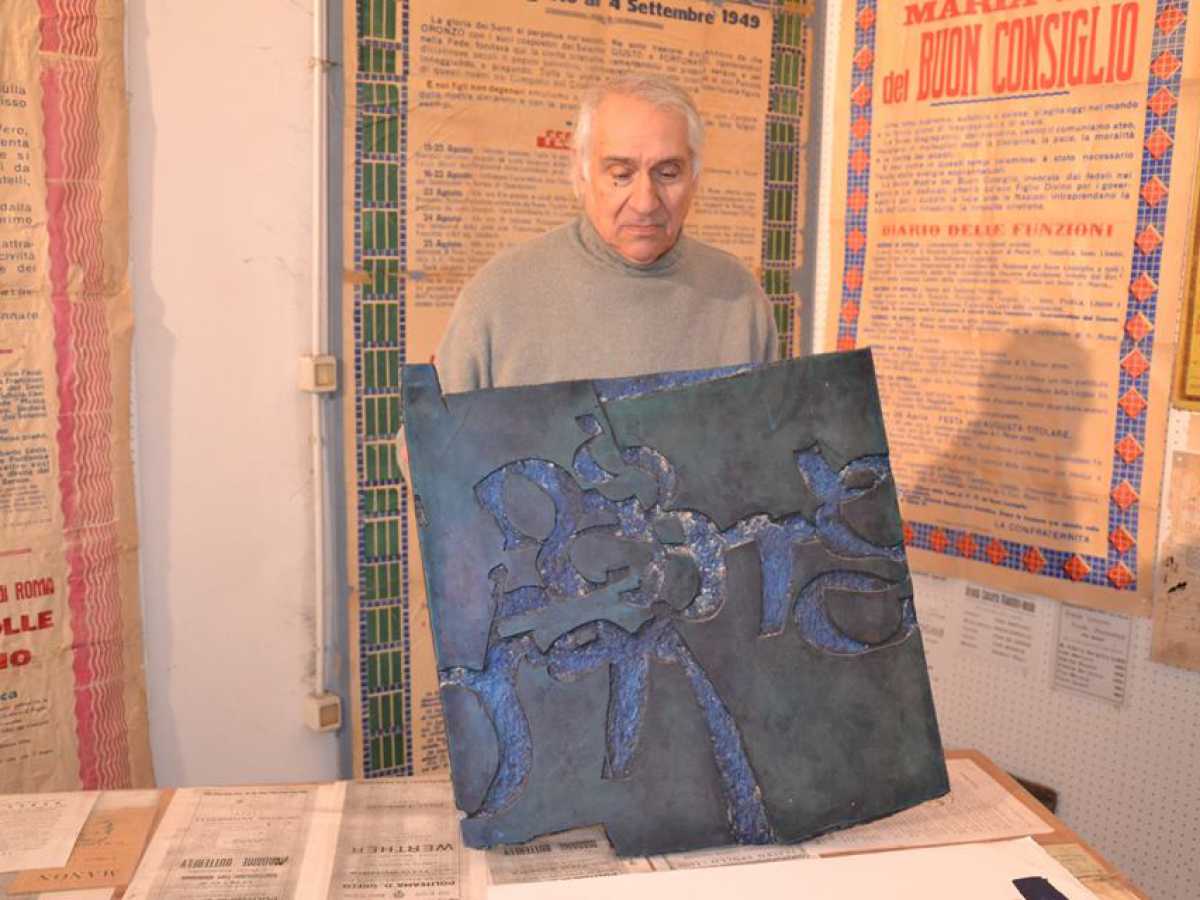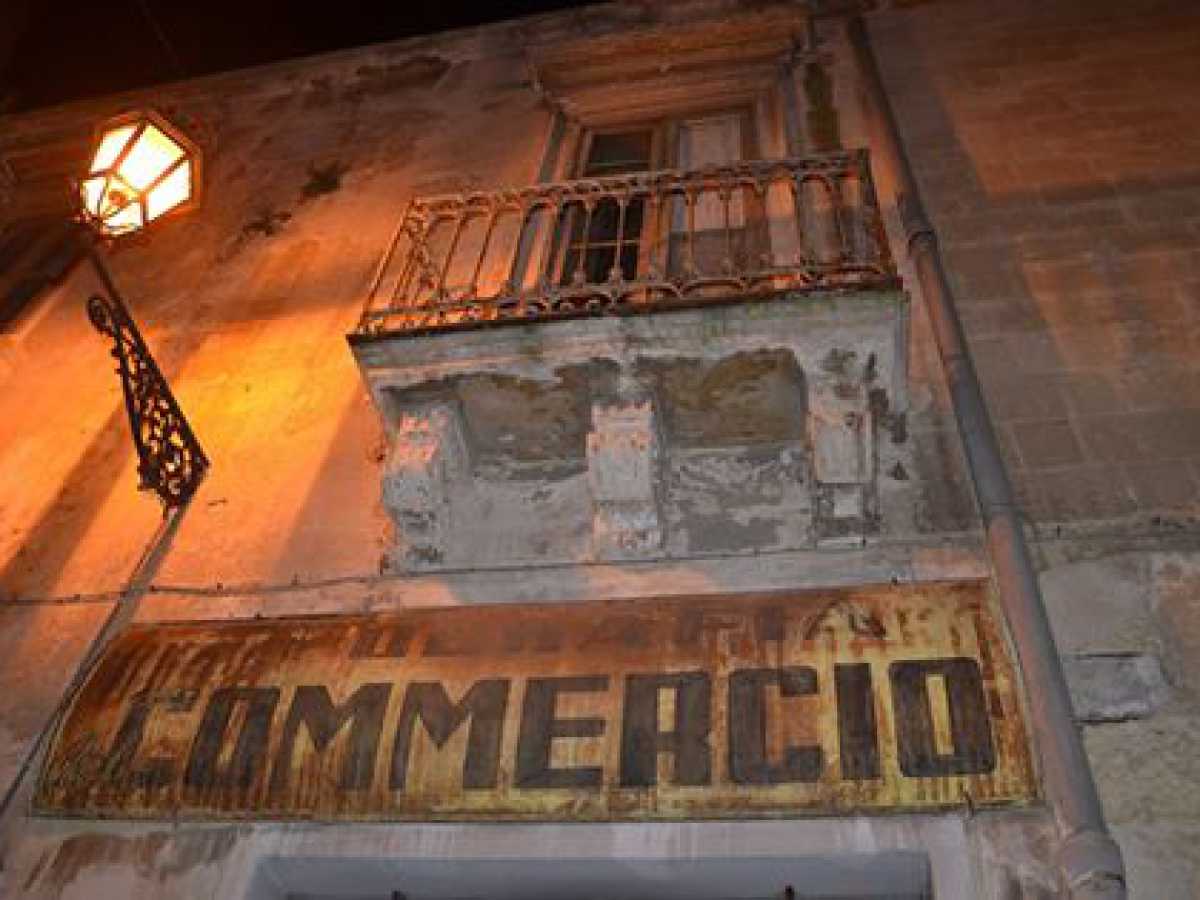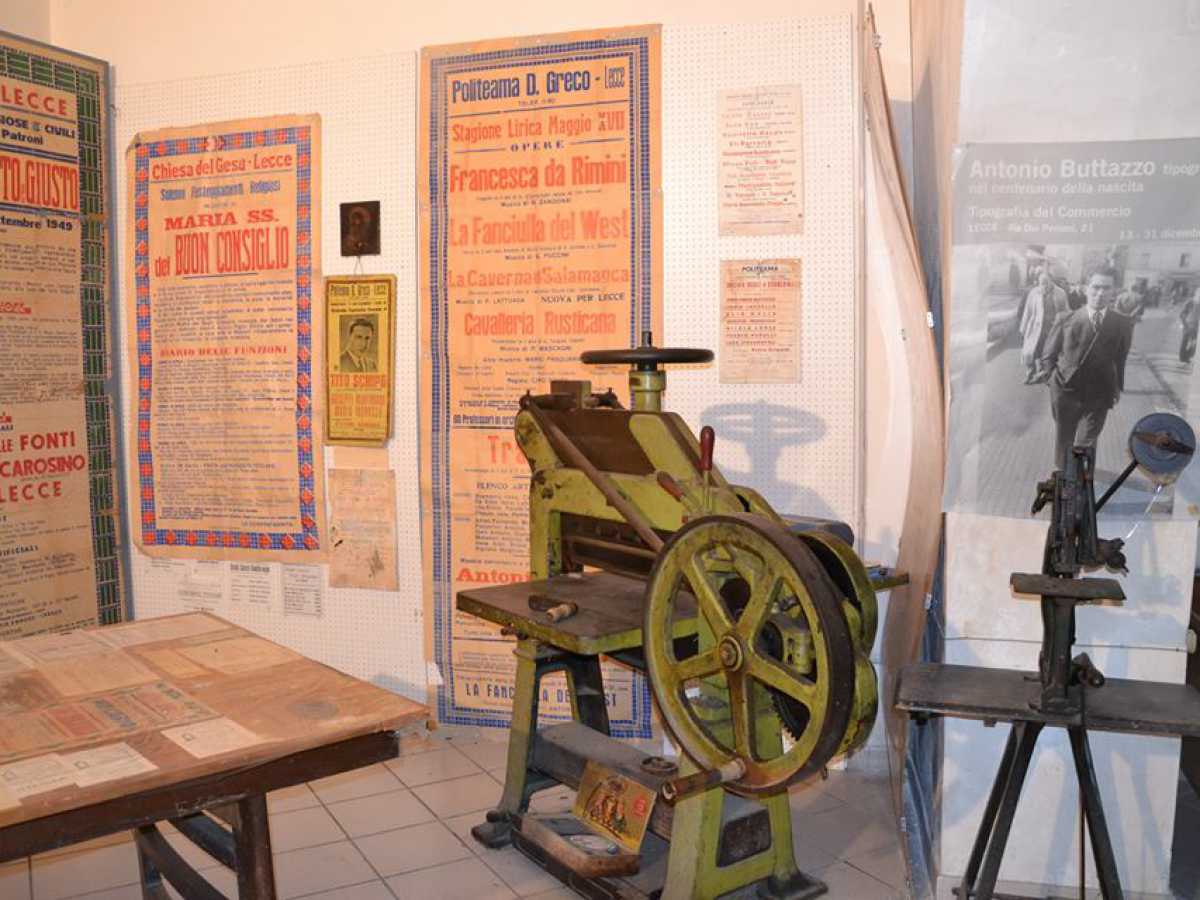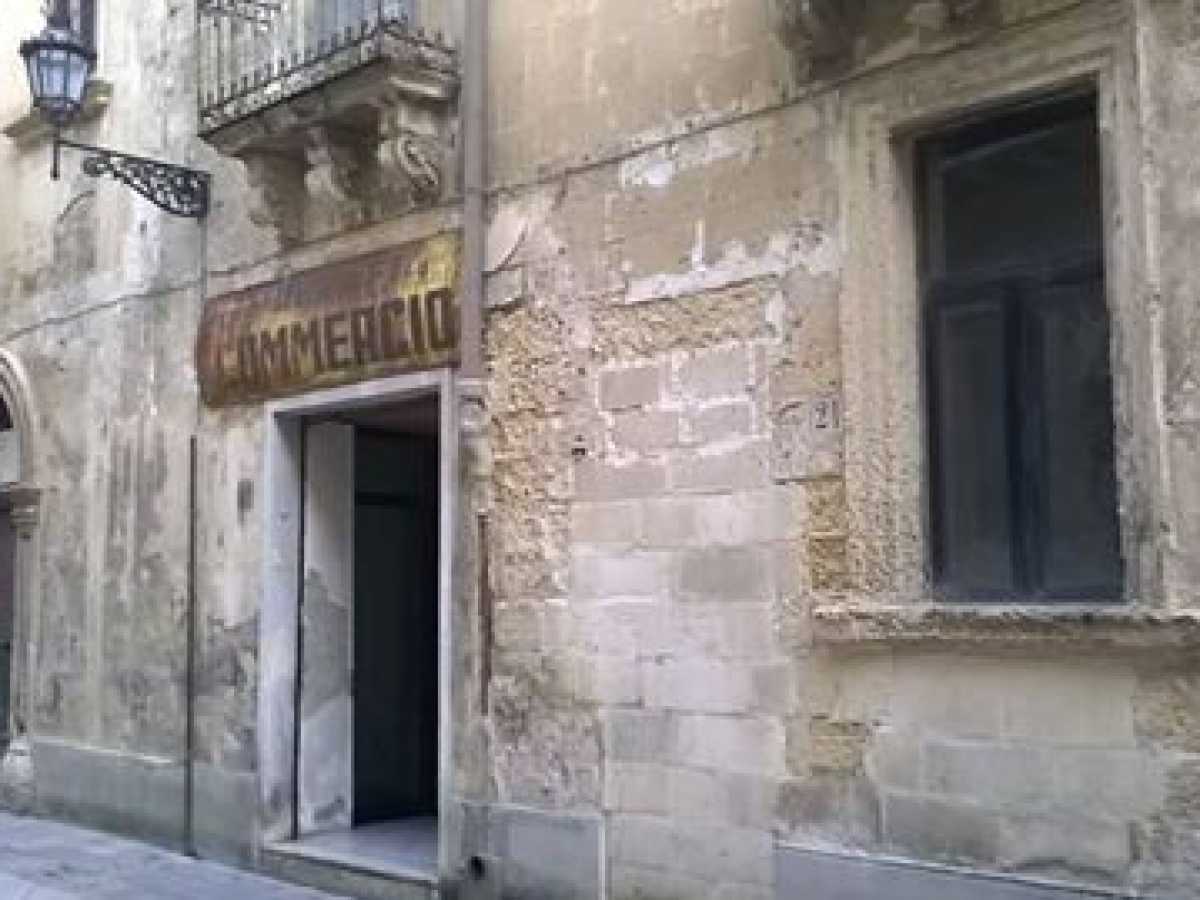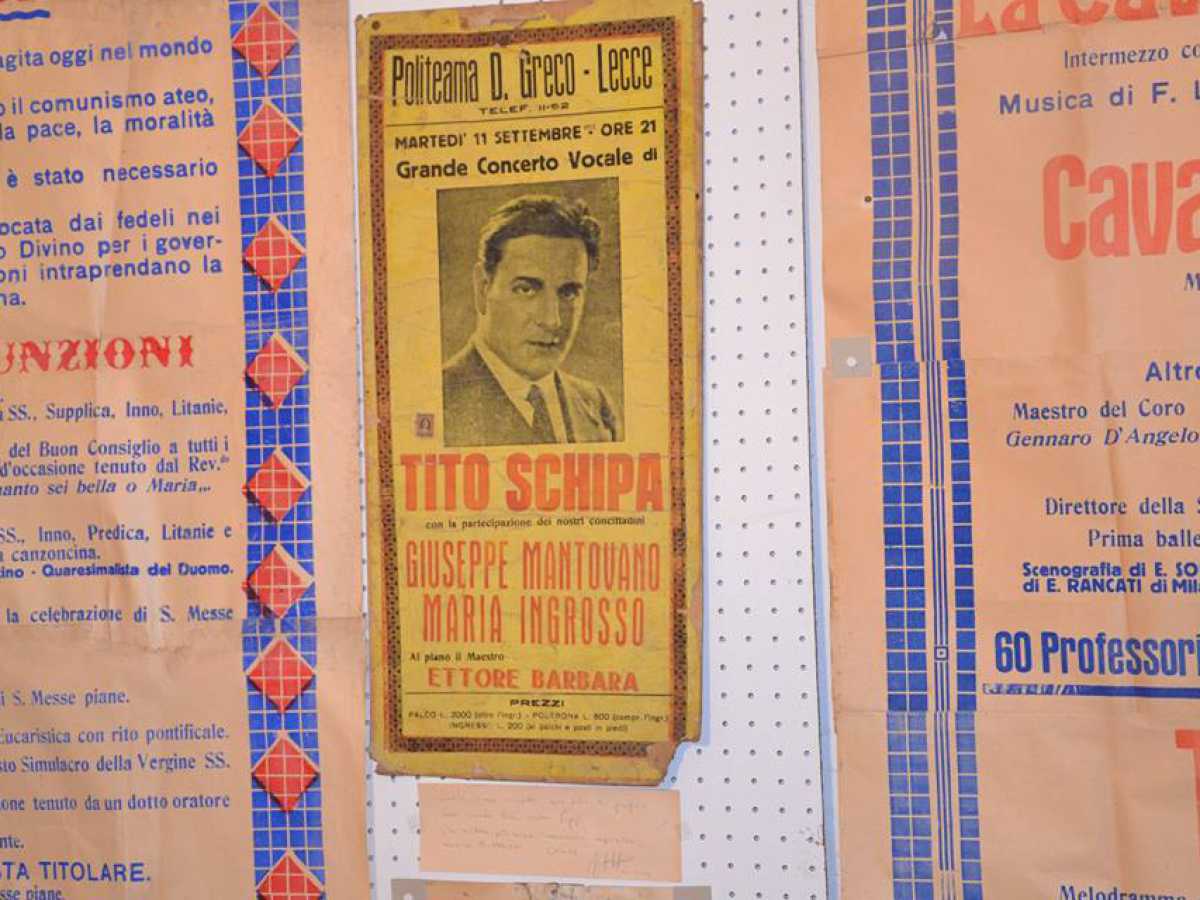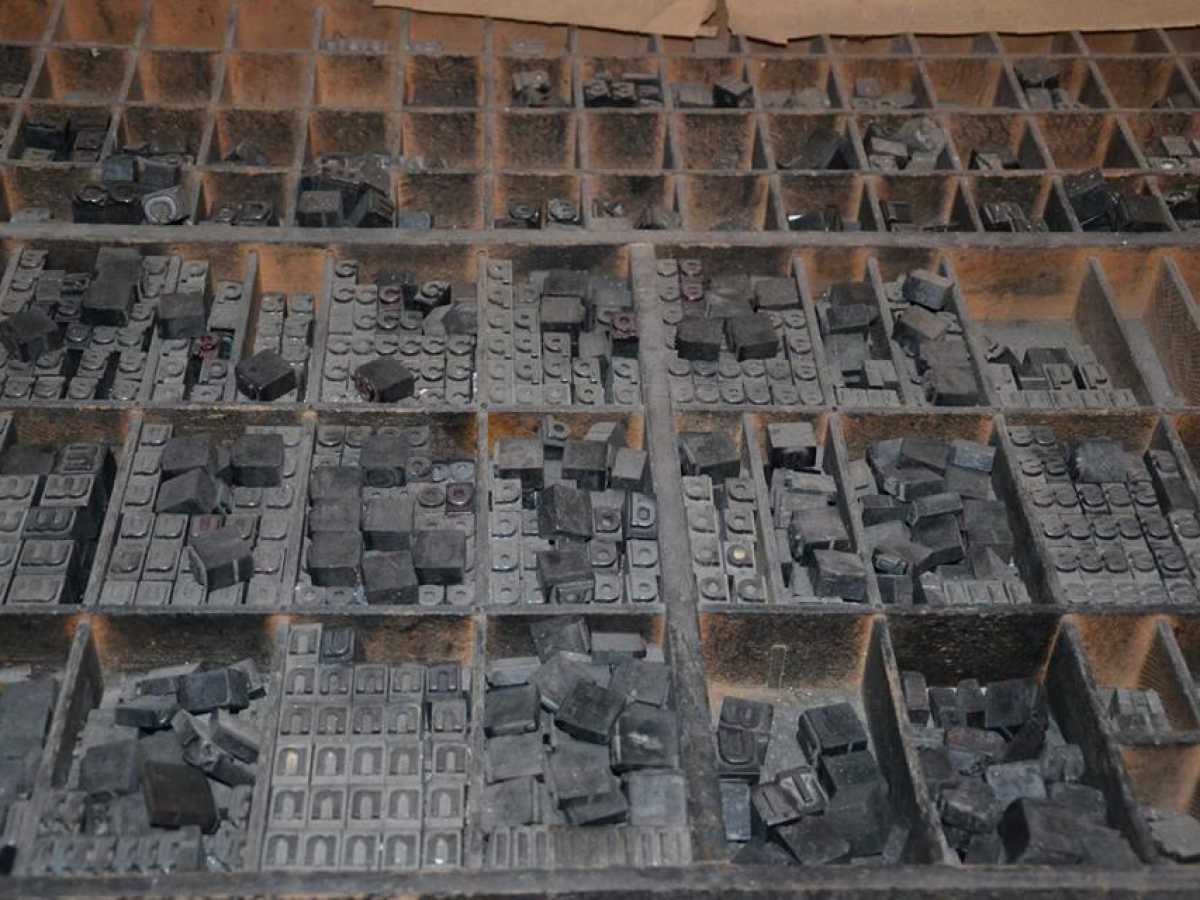
Lecce, la Tipografia del Commercio
L'antica Tipografia del Commercio a Lecce con macchinari dell'800 e del 900 ancora in uso e manifesti e locandine stampate come si faceva una volta, senza l'ausilio dei computer
Il palazzo in cui ha sede la Tipografia del commercio a Lecce in via dei Perroni
L'insegna del 1934, oramai annerita, all'ingresso della tipografia
I caratteri mobili conservati e utilizzati presso la Tipografia del commercio
Esempio dei caratteri formato elefante inventati dal tipografo Antonio Buzzato
La pedalina, macchina azionata con pedale con successiva aggiunta di motore degli anni 20
Una perforatrice di inizi 900 per segmentare i fogli e cesoia manuale con manifesti sullo sfondo
I manifesti di formato elefante e una locandina di feste patronali e spettacoli teatrali con il noto tenore Tito Schipa
Il manifesto di formato elefante con il programma del teatro Politeama leccese
Una locandina cinematografica per il film Il dottor Zivago di David Lean del 1965
Il titolare attuale della Tipografia del commercio Alberto Buttazzo che presenta il cliché in linoleum con il gioco di lettere voluto da Carmelo Bene per il suo Gregorio Cabaret dell'800
Il padre di Alberto Buttazzo, Antonio, tipografo innovativo e creativo
Il nonno di Alberto Buttazzo, Umberto, primo fondatore, insieme al figlio Antonio, della tipografia nel 1926